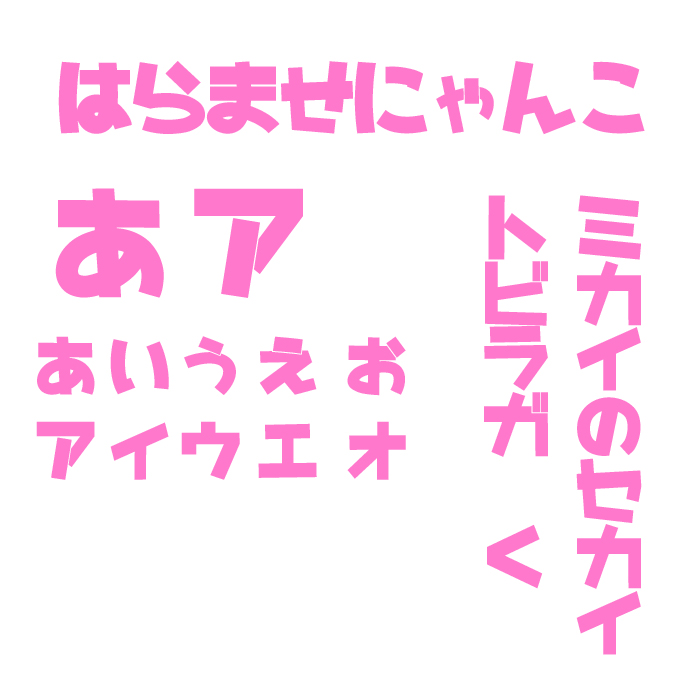
「はらませにゃんこ」フォントは、名前からも連想される可愛らしさと、ポップでコミカルなデザインが特徴のデザインフォントです。
漢字が収録されていないフォントなので、長文の本文には適していないので、タイトルロゴや見出し・キャッチーコピーなどにおすすめのフォントです。
同人誌や漫画、ゲーム製作などのタイトル、ロゴにおすすめのフォントで、マンガなどのオノマトペや擬音語などにも向いているフォントです。
はらませにゃんこフォントの文字見本
収録文字は、ひらがな、カタカナ、英字の他にも、ユニークで楽しい記号が豊富に収録されてます。